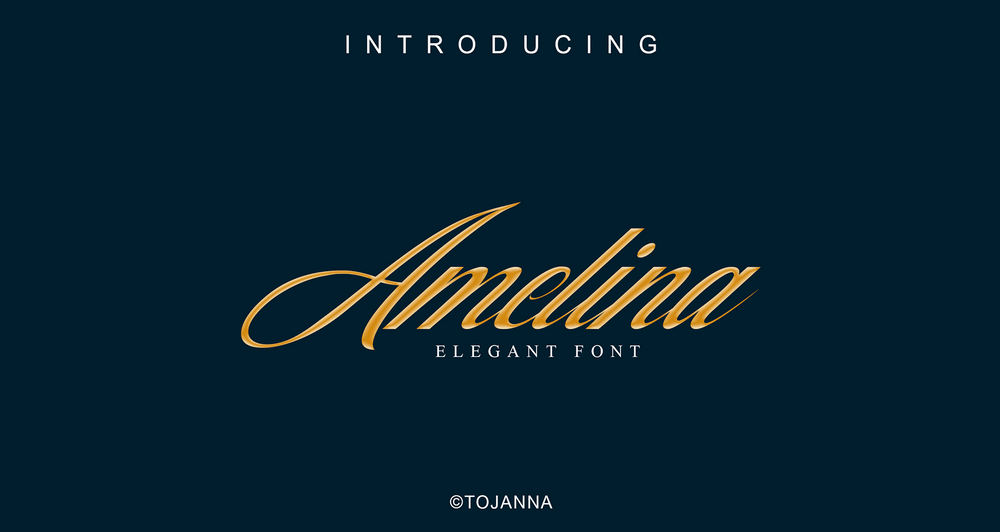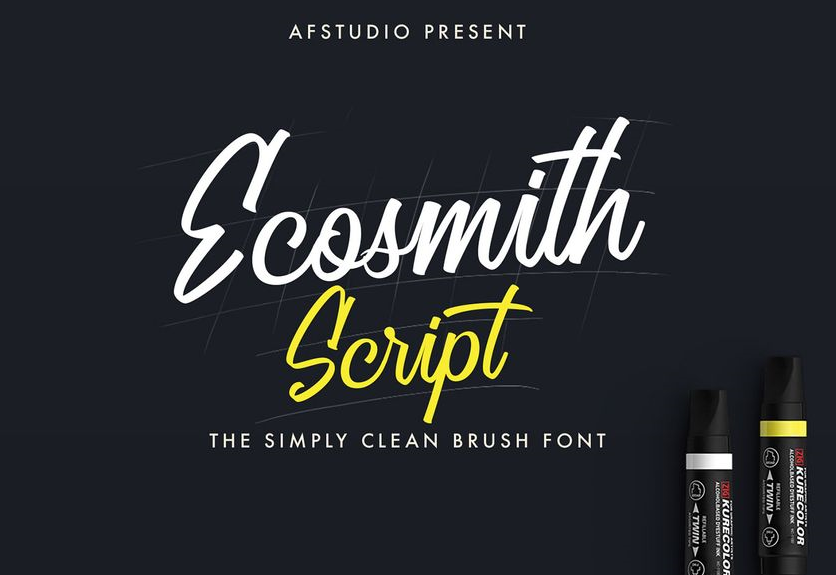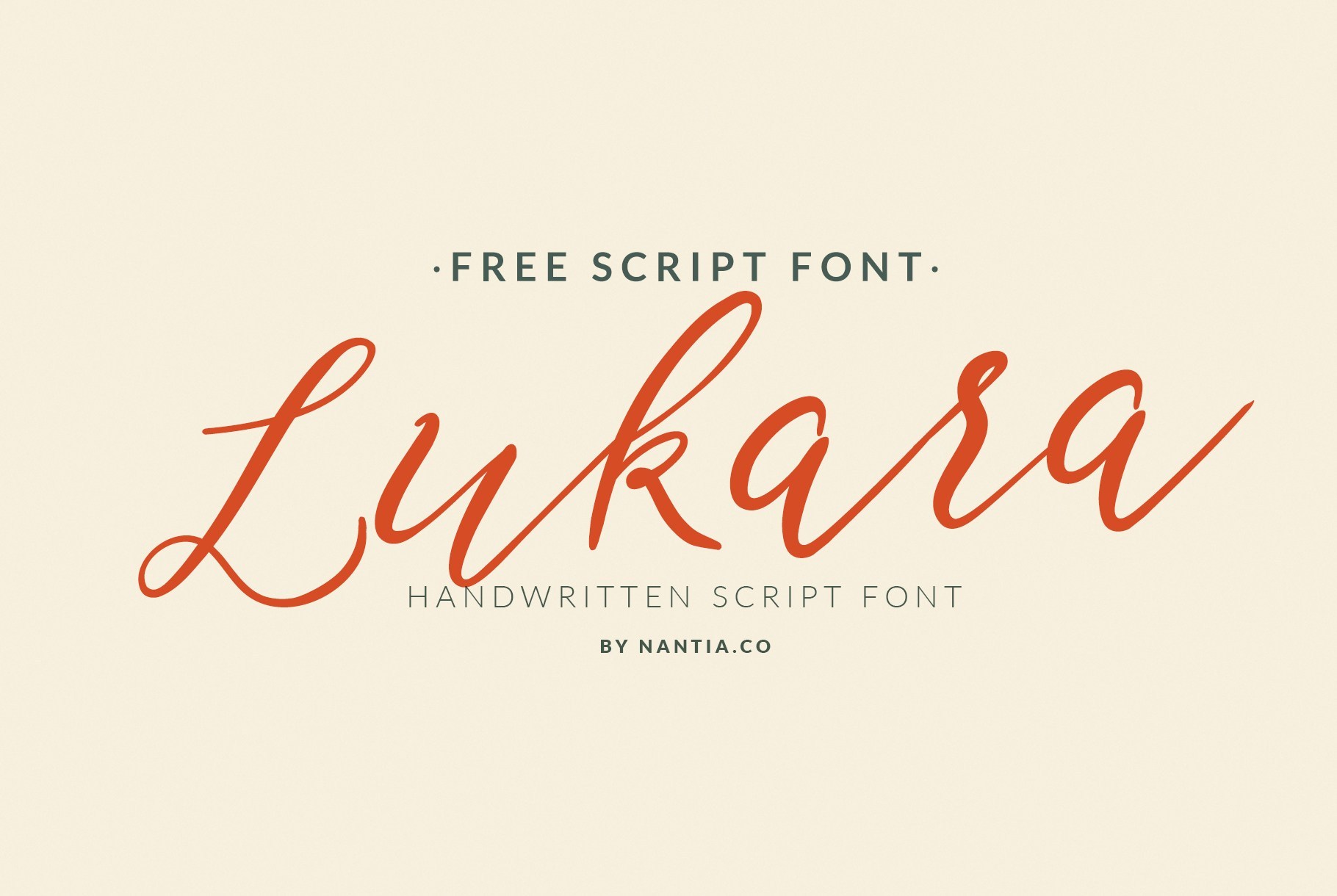
Tổng hơp 100 Font Script đẹp dành cho thiết kế
Font Script là nhóm font mô phỏng nét chữ viết tay, thường có các đường nét mềm mại, nối liền giữa các ký tự. Đây là kiểu chữ mang lại cảm giác gần gũi, tự nhiên và thường gợi liên tưởng đến những dòng viết tay cá nhân, sang trọng hoặc cảm xúc.
Đặc điểm nổi bật của Font Script
• Đường nét uyển chuyển: Các chữ cái thường được nối liền mạch, tạo sự liền lạc và mượt mà trong toàn bộ văn bản.
• Tính cách nhân cao: Mỗi font script có thể mang tính cách khác nhau từ nhẹ nhàng, lãng mạn đến phóng khoáng, nghệ sĩ.
• Phong phú về phong cách: Có thể chia thành các phong cách như: cổ điển (calligraphy), hiện đại (modern script), năng động (casual script) hay phá cách (brush script).
• Độ phức tạp cao: Do đặc trưng về đường nét và cách liên kết ký tự, font script thường được dùng ở tiêu đề hoặc thiết kế đặc biệt, thay vì văn bản dài.
Ứng dụng của Font Script
• Thiết kế thiệp cưới, thiệp mời: Font script là lựa chọn hàng đầu khi cần sự thanh lịch, trang trọng, mang nét cá nhân hóa.
• Logo thương hiệu cá nhân, thời trang, mỹ phẩm: Với cảm giác thủ công và sang trọng, font script rất phù hợp cho các thương hiệu hướng đến sự cao cấp hoặc nữ tính.
• Typography nghệ thuật: Các poster truyền cảm hứng, trích dẫn nổi bật hay typography thường sử dụng font script để thể hiện cảm xúc và chất nghệ sĩ.
• Ấn phẩm truyền thông như banner, poster, bìa sách: Font script giúp tạo điểm nhấn và thu hút ánh nhìn ở những vị trí quan trọng.
• Thiết kế bao bì sản phẩm: Đặc biệt là các sản phẩm thủ công, đồ ăn vặt, bánh kẹo, mỹ phẩm handmade… font script giúp tăng tính cảm xúc và gần gũi.
Font Script là lựa chọn lý tưởng cho các thiết kế cần sự tinh tế, cá tính và cảm xúc. Với vẻ đẹp nghệ thuật và sự đa dạng trong phong cách thể hiện, font script giúp bạn kể những câu chuyện bằng hình ảnh một cách duyên dáng và đầy cảm hứng.